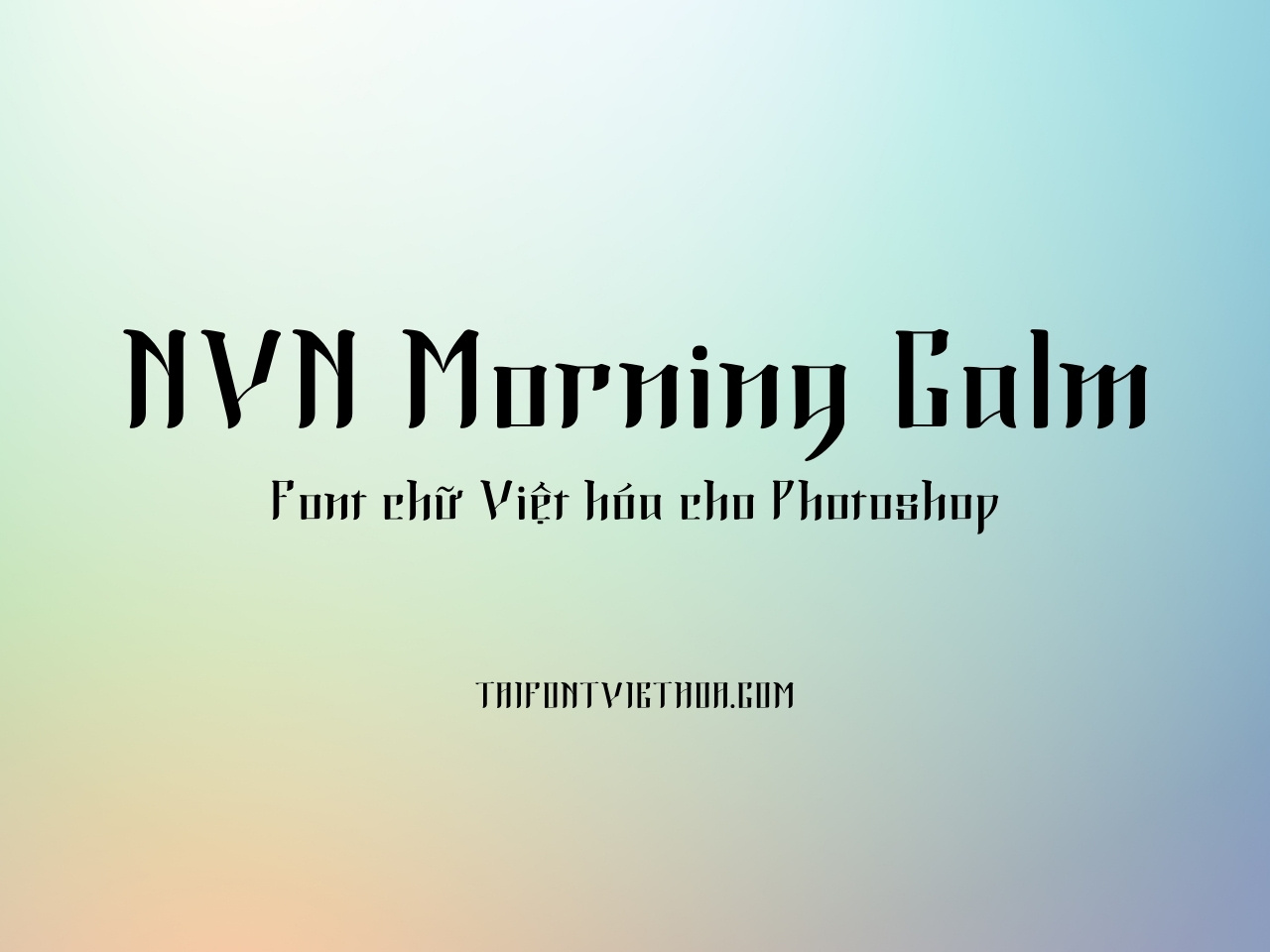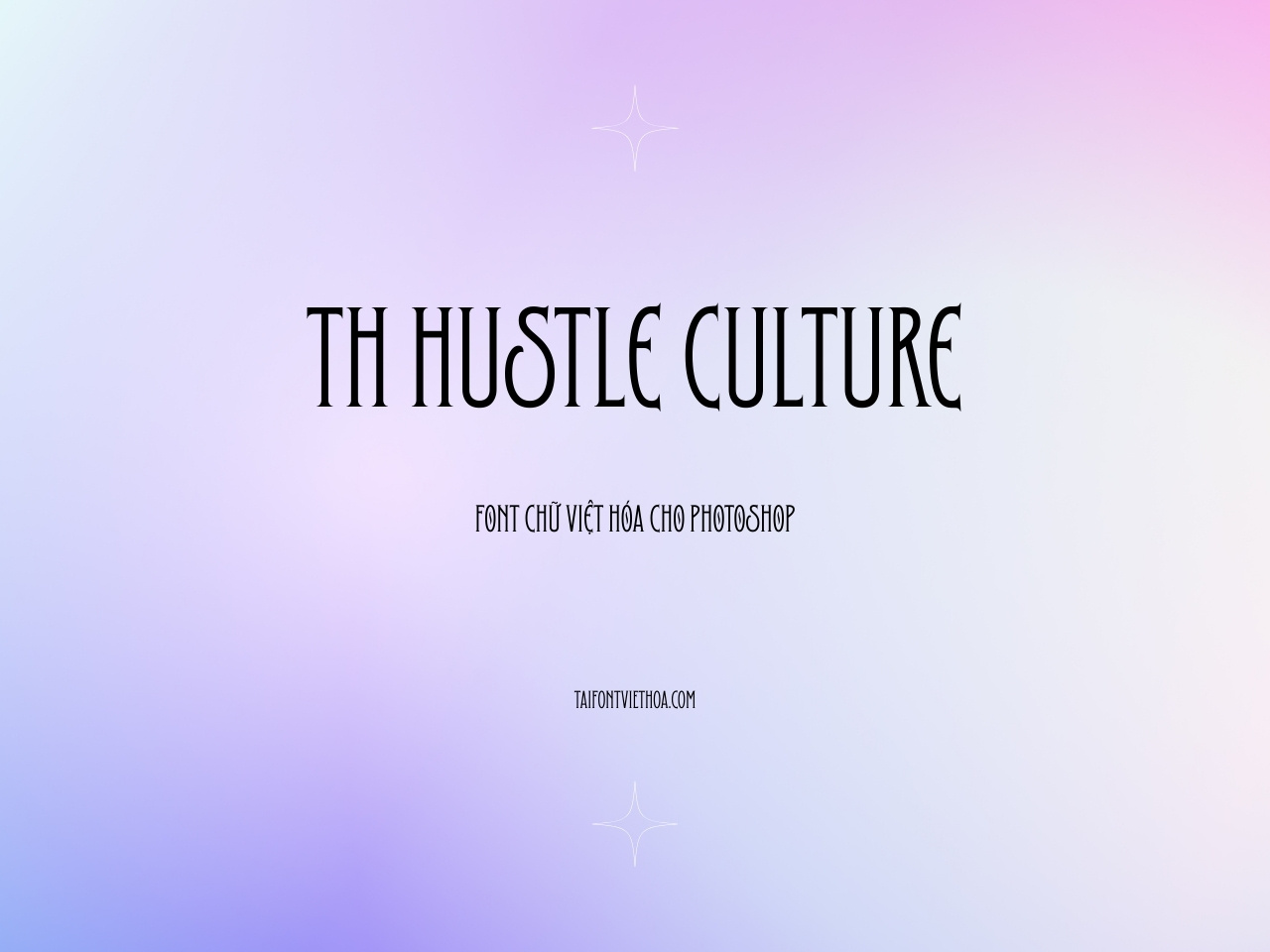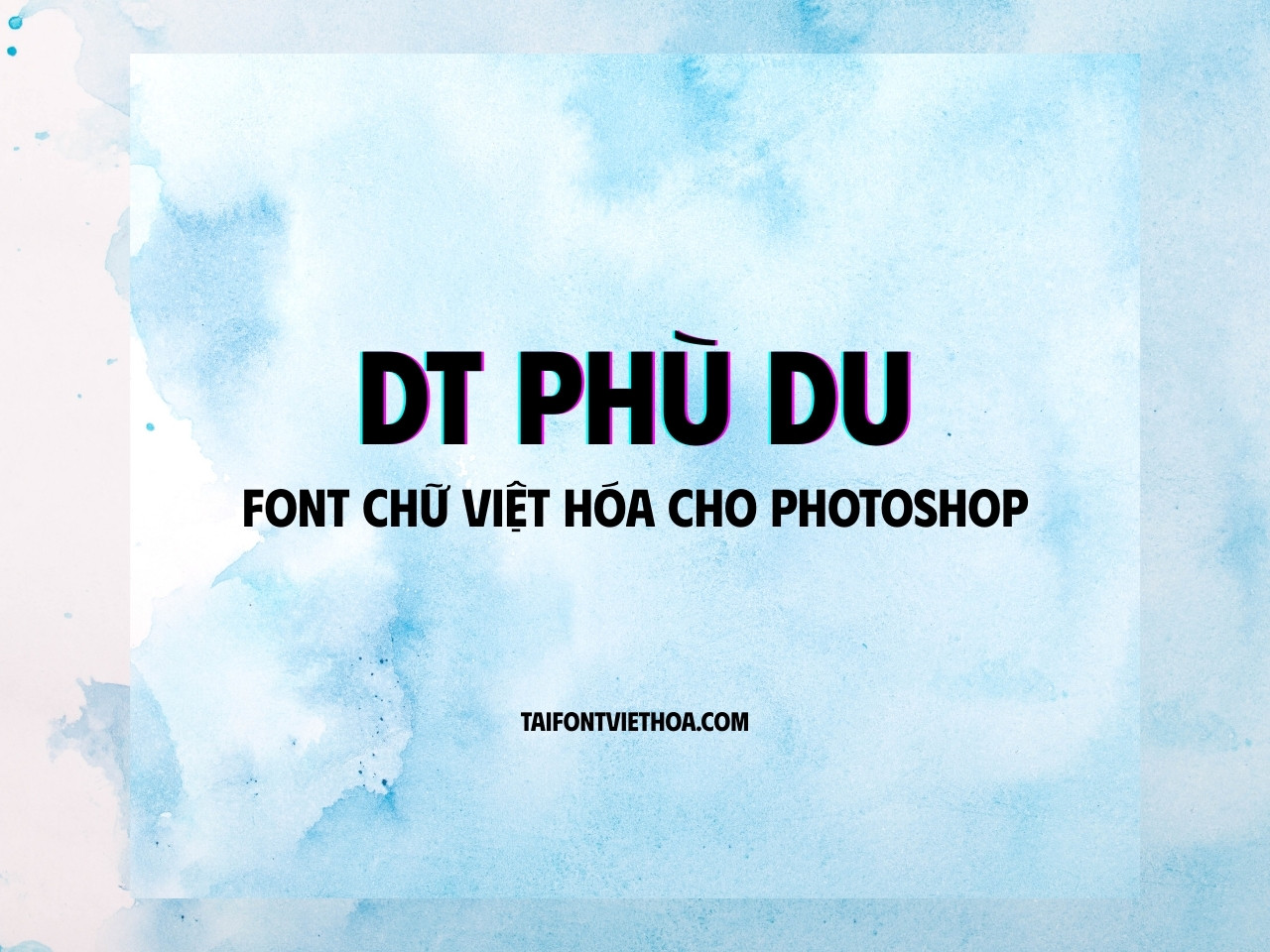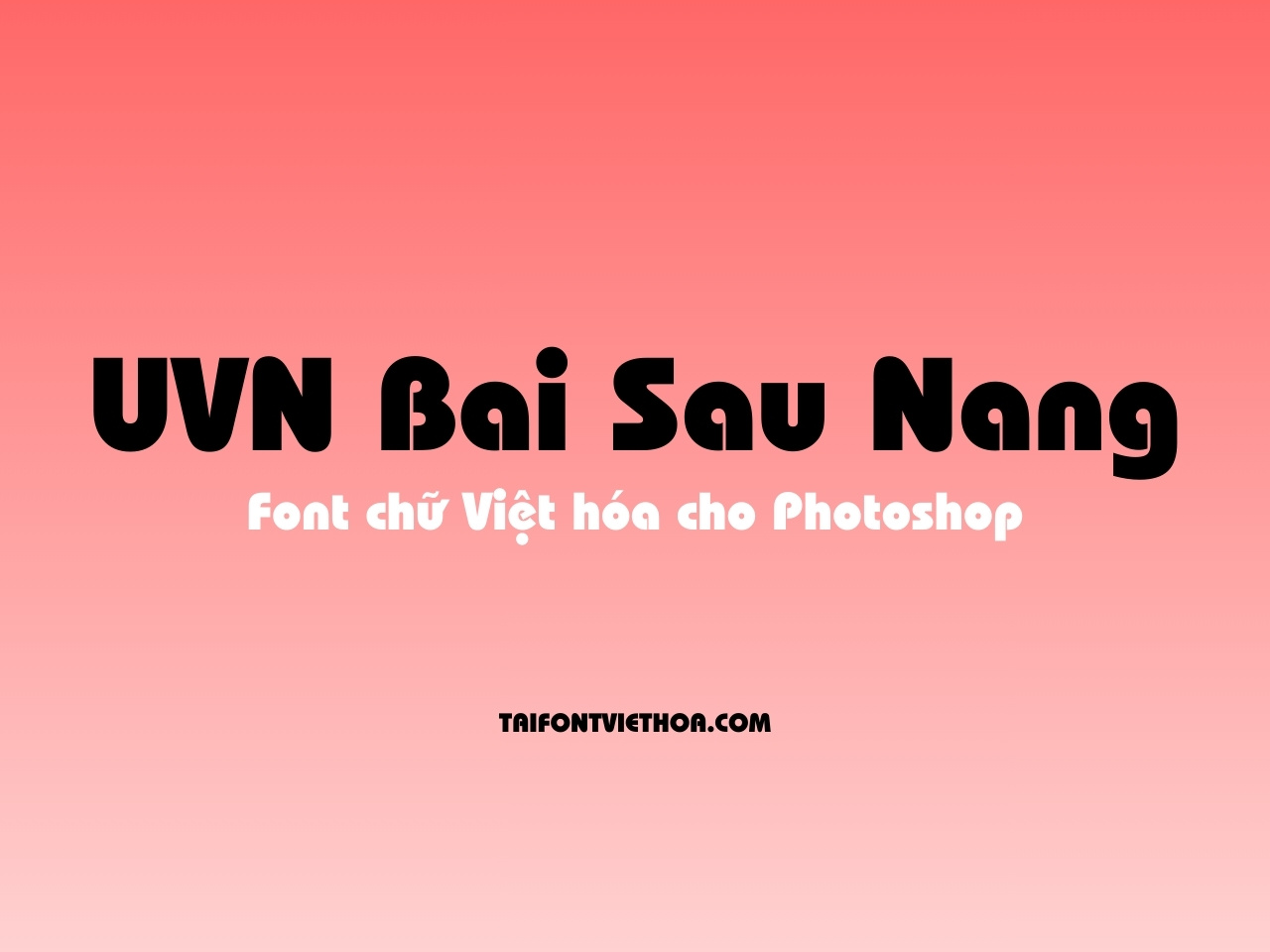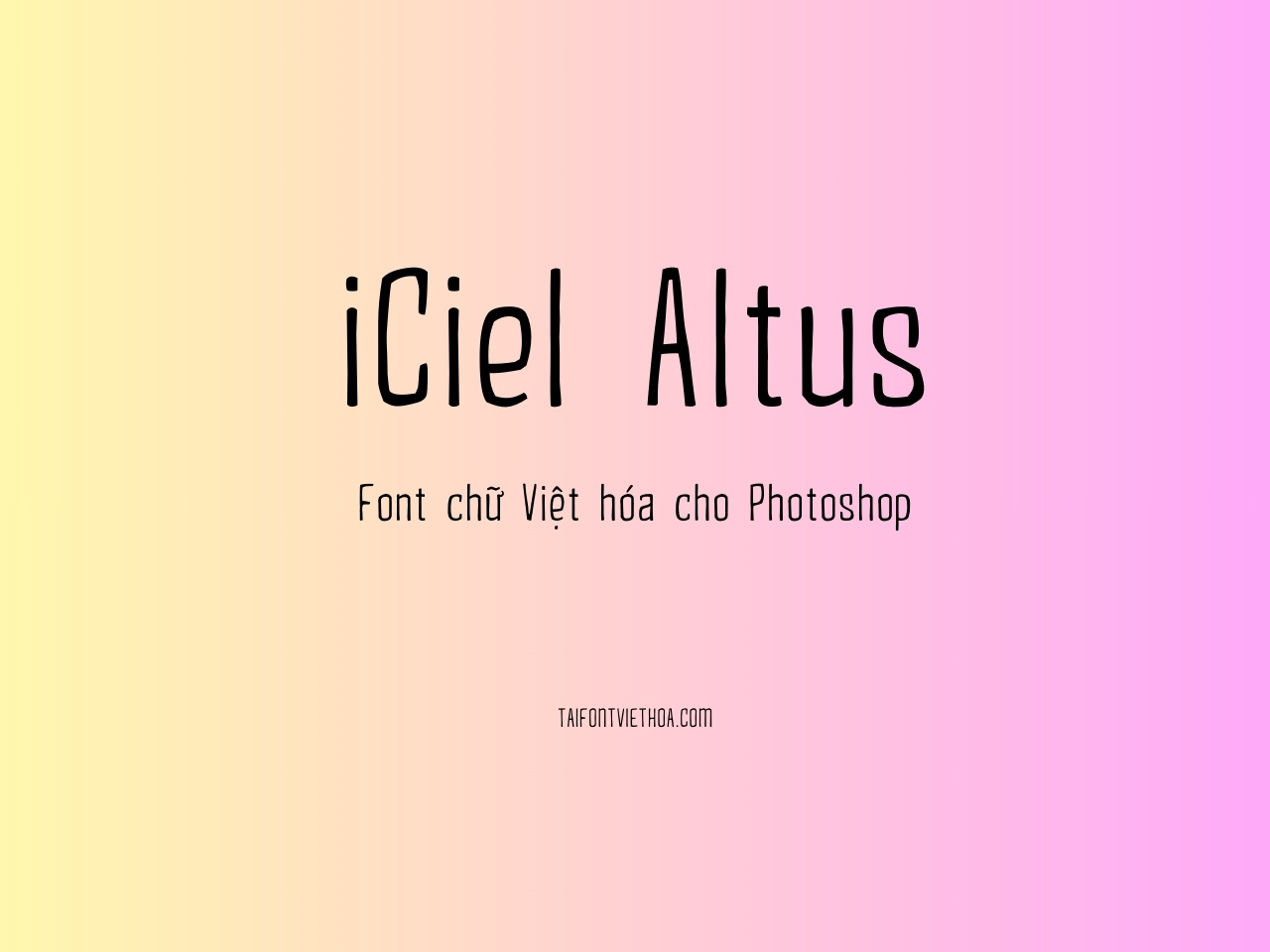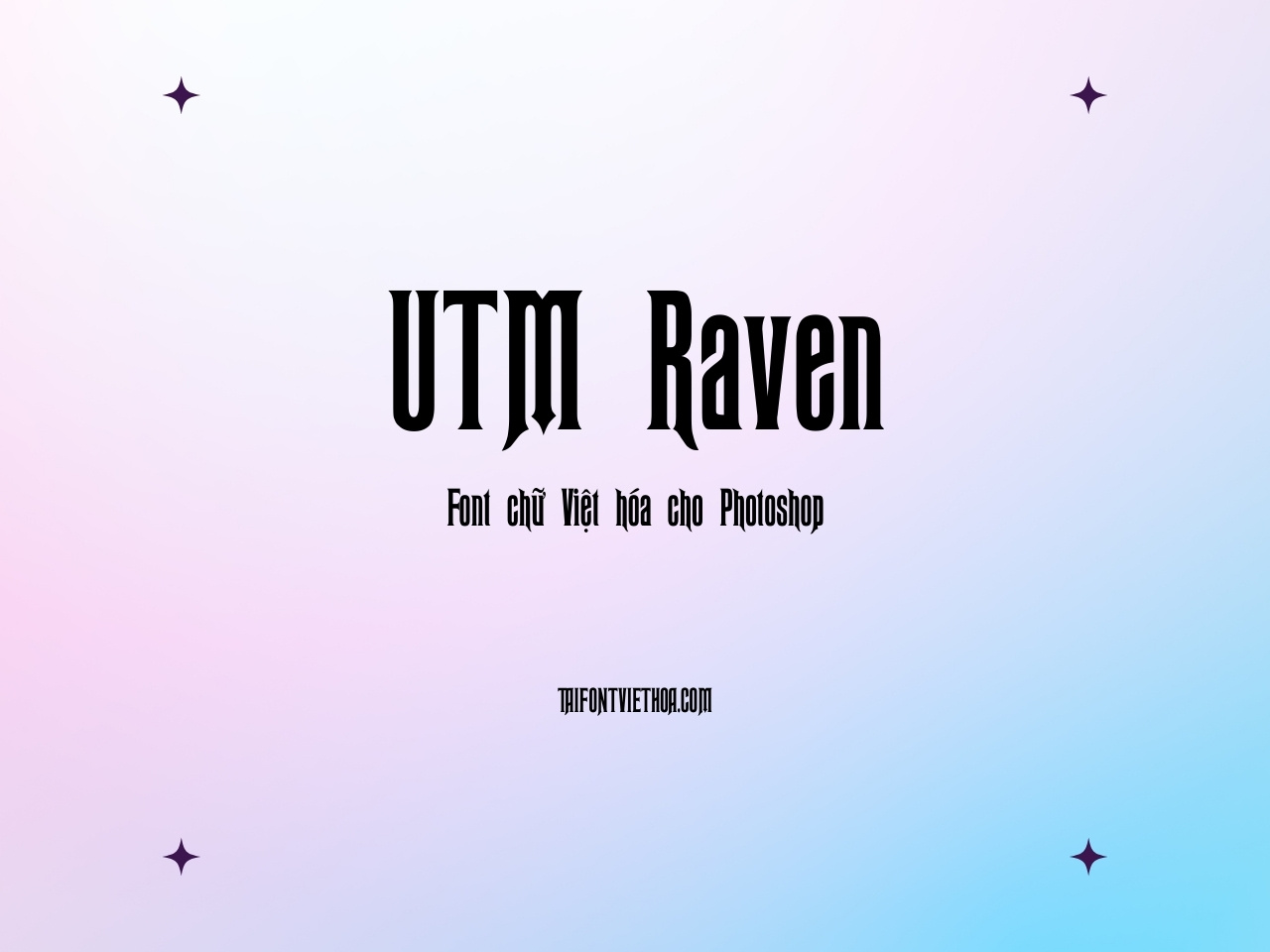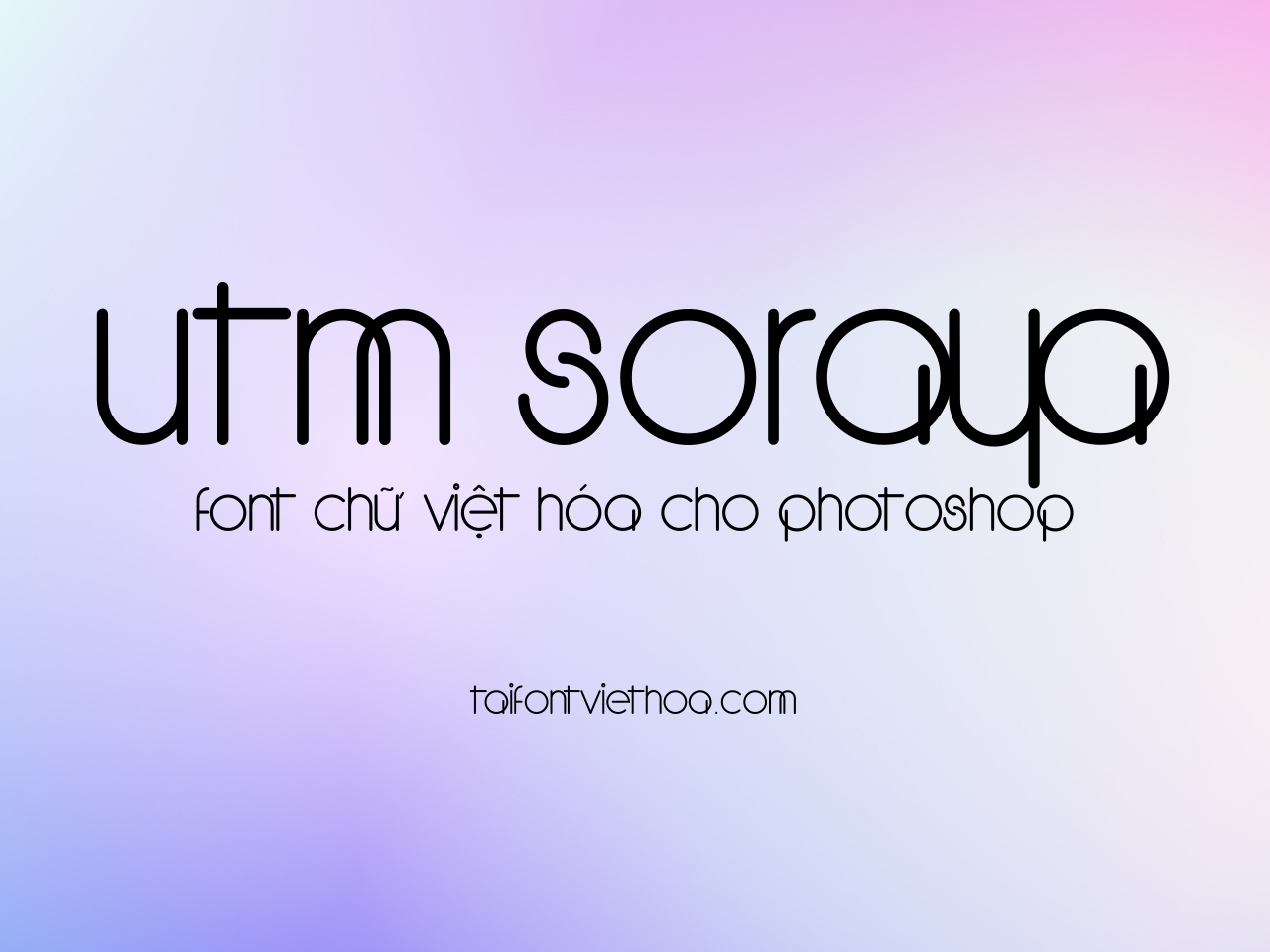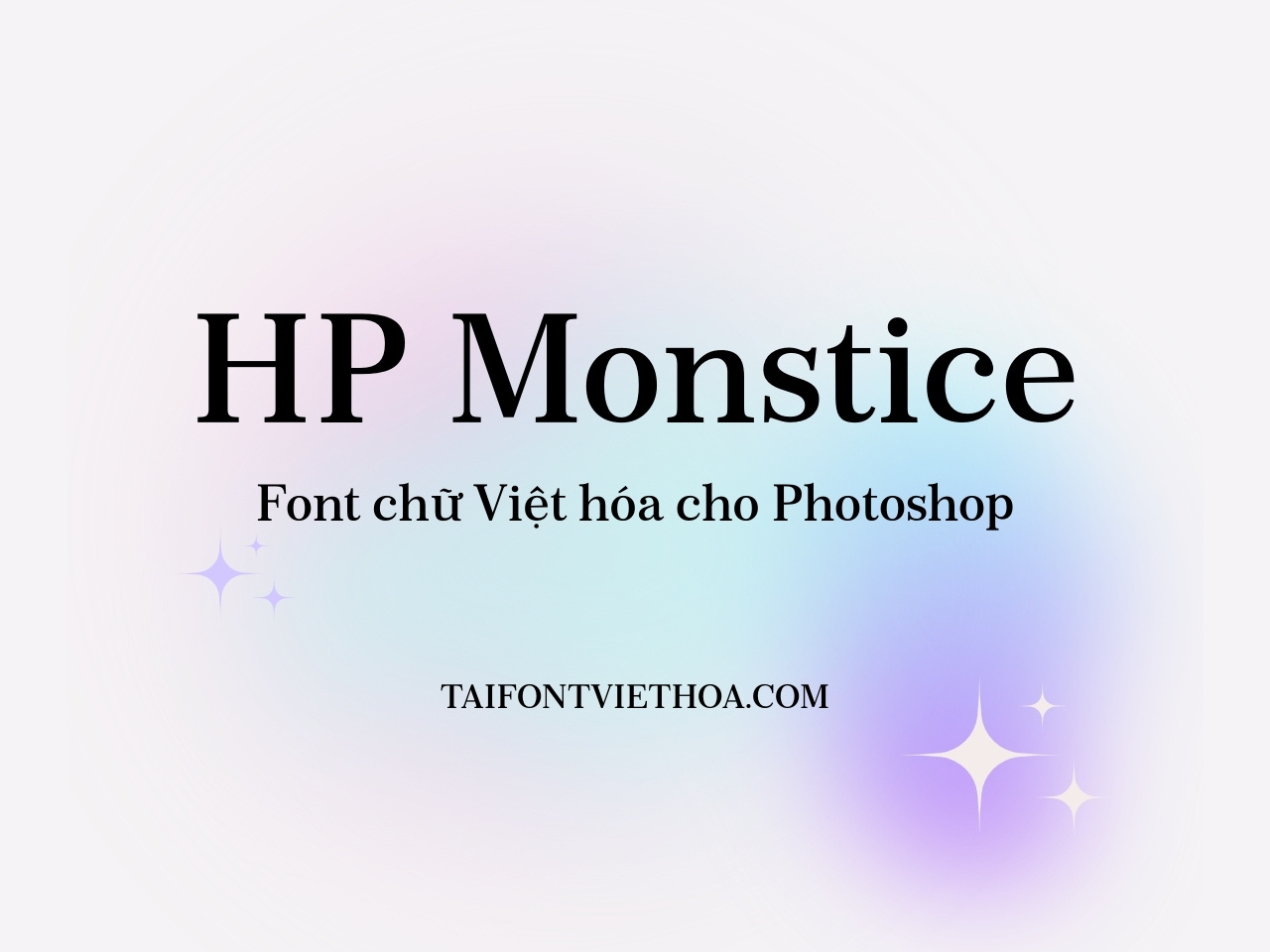
Trong thiết kế, Font chữ Việt hóa cho Photoshop ngày càng trở thành lựa chọn cần thiết. Các font cơ bản như Unicode, VNI, UTM… tuy thông dụng nhưng dễ gây nhàm chán, trong khi nhiều font đẹp tải về lại không hỗ trợ gõ dấu tiếng Việt. Vì vậy, việc dùng font Việt hóa – hỗ trợ đầy đủ ký tự tiếng Việt – chính là giải pháp giúp designer tạo nên những tác phẩm chuyên nghiệp và ấn tượng.
Font chữ Việt hóa cho Photoshop là gì? Vì sao quan trọng?
Font chữ là tập hợp đầy đủ các chữ cái, chữ số, ký tự đặc biệt… tuân theo một kiểu thiết kế thống nhất về hình dạng và kích cỡ. Font chữ Việt hóa là thuật ngữ chỉ những font chữ đã được bổ sung đầy đủ dấu và ký tự Unicode tiếng Việt, cho phép gõ tiếng Việt có dấu một cách chính xác. Điều này đặc biệt quan trọng vì nếu font không hỗ trợ Unicode tiếng Việt, văn bản sẽ bị lỗi dấu hoặc không hiển thị đúng chữ tiếng Việt. Hầu hết các font Việt hóa hiện đại đều sử dụng bảng mã Unicode, giúp tương thích với các bộ gõ như Unikey.
Tầm quan trọng
Font chữ Việt hóa cho Photoshop giúp giải quyết triệt để việc hiển thị tiếng Việt: gõ đủ dấu, không méo ký tự. Nhờ đó, bạn giữ được tính chuyên nghiệp và nhất quán thị giác cho poster, banner, social post hay video. Đồng thời, bộ font Việt hóa đa dạng giúp thoát khỏi vòng lặp các font mặc định nhàm chán, rút ngắn thời gian kiểm tra và hạn chế phải đổi font vào phút chót.
Font chữ Việt hóa cho Photoshop là gì? Vì sao quan trọng?
Lợi ích khi sử dụng Font chữ Việt hóa cho Photoshop
• Hiển thị chuẩn tiếng Việt: Bộ ký tự đầy đủ trong định dạng TrueType/OpenType bảo đảm văn bản tiếng Việt render chính xác trên Windows/macOS, tránh méo dấu khi scale, transform hoặc áp hiệu ứng trong Photoshop.
• Đa dạng phong cách: Bạn có thể linh hoạt chọn serif trang trọng, sans-serif hiện đại, script/handwritten giàu cảm xúc, display/retro nổi bật hay monospace kỹ thuật – phù hợp từ logo, tiêu đề, poster đến UI mockup.
• Tối ưu quy trình sáng tạo: Hạn chế “đổi font phút chót” do thiếu dấu; giữ nhịp làm việc liên tục khi phối hợp giữa Photoshop – Illustrator – Premiere/After Effects; dễ tạo hệ thống typographic scale nhất quán cho toàn bộ chiến dịch.
• Tương thích và nhập liệu mượt: Hoạt động ổn định với bộ gõ Unikey/VietKey theo chuẩn Unicode; hạn chế lỗi khi paste nội dung từ Word/Docs sang Photoshop; hỗ trợ variable fonts (nếu có) để tinh chỉnh weight/width linh hoạt mà không phải cài quá nhiều file.
Font chữ Việt hóa cho Photoshop là nền tảng giúp bạn truyền tải thông điệp bằng tiếng Việt một cách chính xác, đẹp mắt và hiệu quả – vừa nâng chất lượng thẩm mỹ, vừa rút ngắn thời gian sản xuất thiết kế.
Lưu ý khi chọn font chữ Việt hóa cho thiết kế đồ họa
• Phù hợp với nội dung và thương hiệu: Mỗi thiết kế cần một kiểu font hài hòa với thông điệp. Ví dụ, font chữ mềm mại, uốn lượn hợp với thiệp mời hoặc poster nghệ thuật, trong khi font chữ hiện đại tối giản hợp với thiết kế tối giản, công nghệ. Hãy cân nhắc tính cách thương hiệu và đối tượng người xem khi chọn font (serif tạo cảm giác trang trọng, sans-serif gợi sự hiện đại, font thư pháp mang nét nghệ thuật dân tộc, v.v.).
• Đảm bảo tính đọc dễ dàng: Dù thiết kế sáng tạo, font chữ vẫn phải rõ ràng, dễ đọc ở các kích thước khác nhau. Tránh lạm dụng font quá cầu kỳ cho đoạn văn dài; thay vào đó dùng font trang trí cho tiêu đề, còn nội dung chính dùng font đơn giản hơn để người xem thoải mái đọc.
• Kiểm tra hỗ trợ tiếng Việt: Luôn ưu tiên font không lỗi tiếng Việt, tức font đã Việt hóa đầy đủ dấu và ký tự. Trước khi dùng, hãy gõ thử các chữ cái dấu (ă, ê, ồ, ử, đ, etc.) để chắc chắn font hiển thị đúng. Một số font Việt hóa uy tín giúp bạn viết tiếng Việt mà không gặp tình trạng lỗi font – điều này cực kỳ quan trọng để thiết kế trông chuyên nghiệp và chỉn chu.
• Kết hợp font hài hòa: Trong một thiết kế, có thể kết hợp 2-3 font chữ khác nhau (ví dụ tiêu đề, nội dung, chú thích) nhưng cần thống nhất phong cách. Một typography hài hòa thường gồm một font chính và một font phụ bổ trợ, tránh sử dụng quá nhiều font gây rối mắt. Hãy chọn các font bổ sung cho nhau về cả phong cách lẫn kích thước để tổng thể thiết kế cân đối.